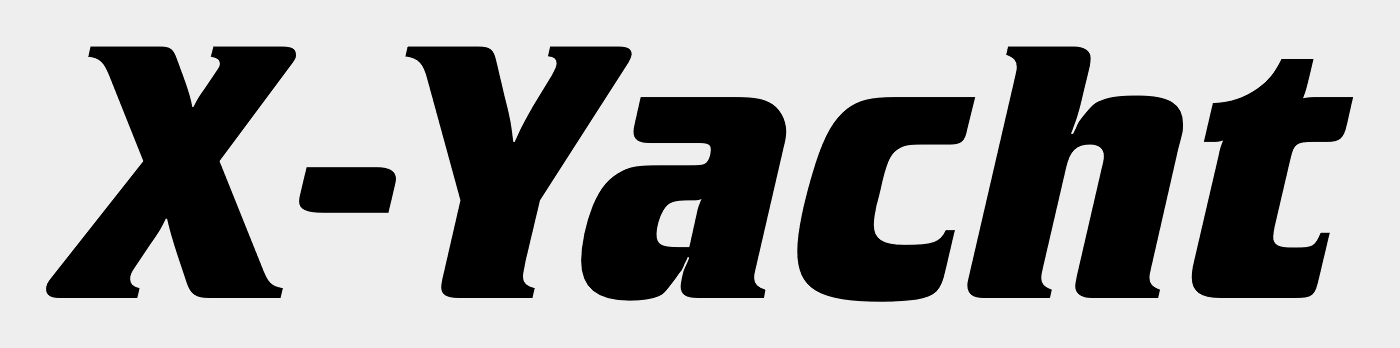
Würdet Ihr auch sagen, dass für das Logo der »X-Yachts« eine leicht bearbeitete Crillee verwendet wird?
Ein Schiffseigner und Besitzer einer solchen X-Yacht möchte den Namen seines Schiffes in derselben Schrift auf seinem Boot haben. Ich würde sagen, es ist eine Letraset Crillee™ Bold Italic, die noch etwas bearbeitet wurde für das X-Yacht Logo.
Oder seht Ihr das anders?x-yachts-logo-black.thumb.png.b160ba76a9c2525092389d7ea7d361e1.png
Yep, die wurde einfach auf 200 % Breite gezogen (und ein wenig rundgelutscht).
Welche Crillee genau (ob Letraset oder eine andere) das war, lässt sich wahrscheinlich nicht sagen.